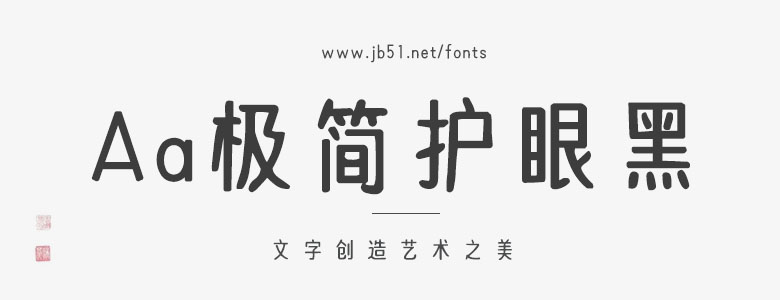
Aa極簡(jiǎn)護(hù)眼黑 2萬字是一款中文字體,這款字體的筆觸較為粗實(shí),字形端正大氣,具有很好的視覺效果,適合應(yīng)用于藝術(shù)設(shè)計(jì)、平面宣傳設(shè)計(jì)、網(wǎng)頁設(shè)計(jì),海報(bào)設(shè)計(jì)等領(lǐng)域,需要的朋友可以前來本站下載。